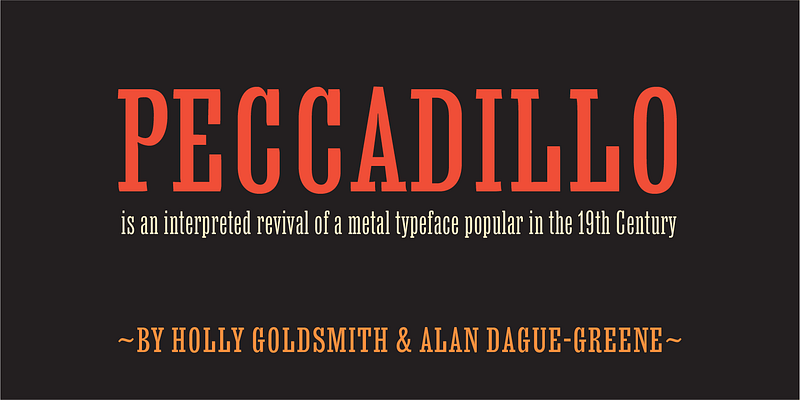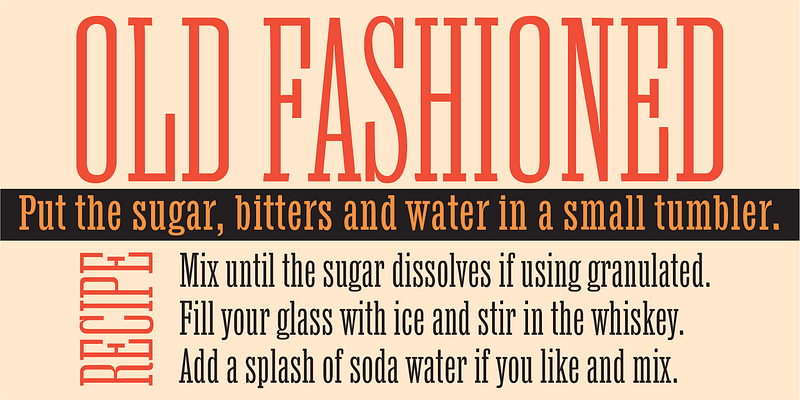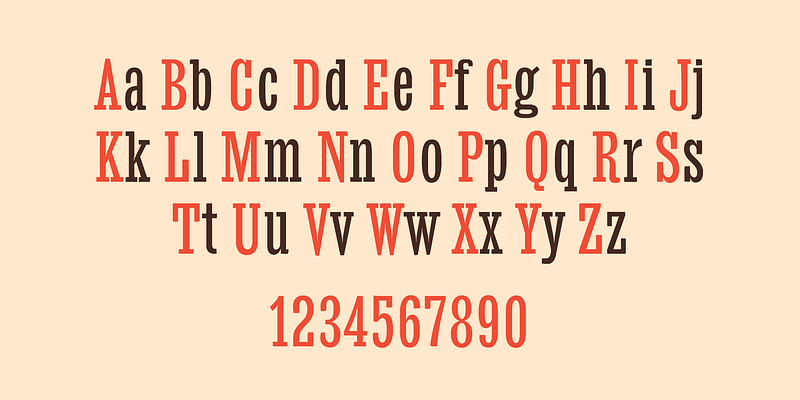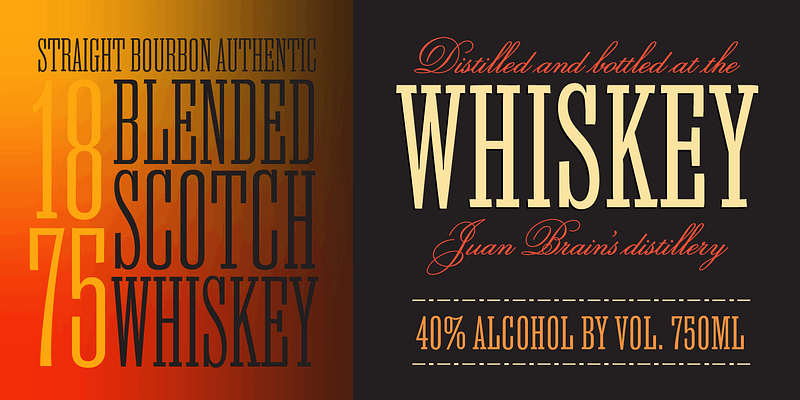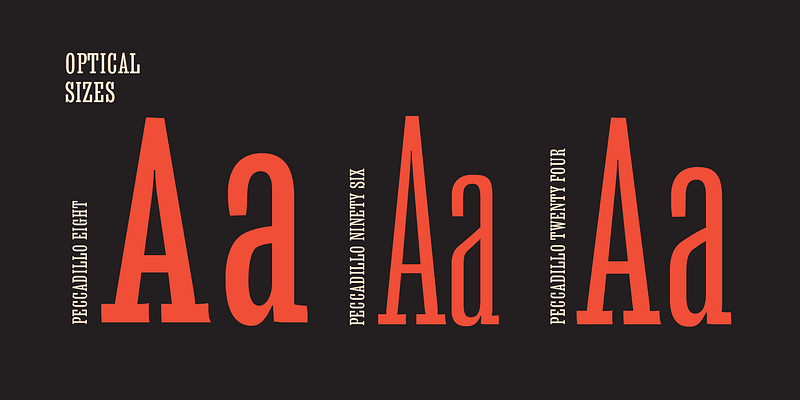
MVB Peccadillo ist eine interpretierte Wiederbelebung einer im 19. Jahrhundert beliebten Metallschrift, damals bekannt als Skeleton Antique. Die Schriftart ist stark kondensiert und hat extra kurze Unterlängen, um auf engem Raum eine große Wirkung zu erzielen.
Holly Goldsmith arbeitete mit im Buchdruck hergestellten Exemplaren der antiken 96-Punkt-Metallschrift und behielt dabei bewusst subtile Verzerrungen bei, die durch die Abnutzung der Schrift und den Buchdruck entstanden. Alan Dague-Greene passte das Design anhand von gedruckten Mustern der Skeleton Antique an, um zwei zusätzliche optische Größen zu schaffen: „Eight“ für kleineren Text und „Twenty-four“ für Zwischenüberschriften.